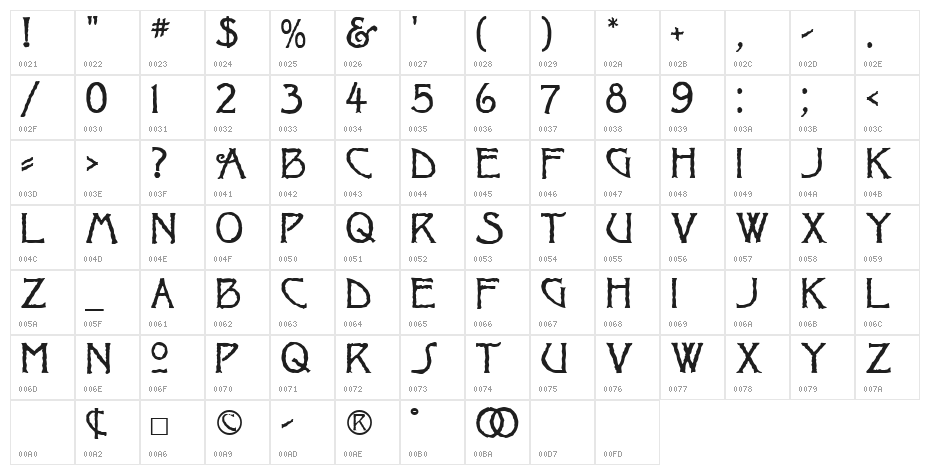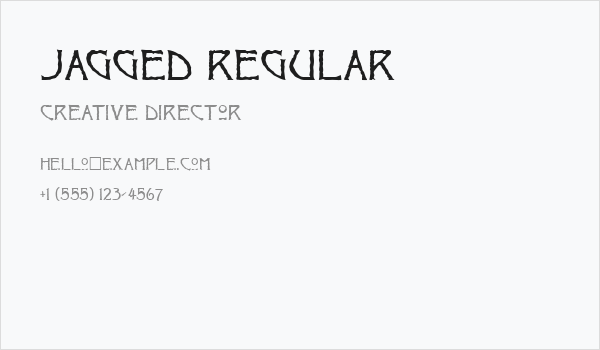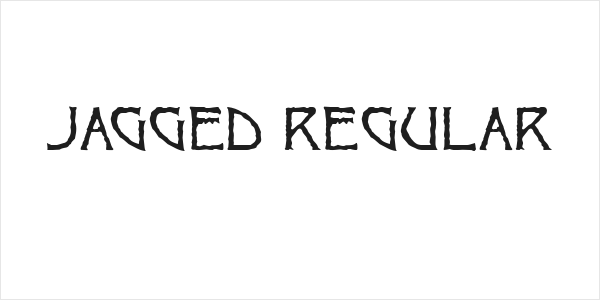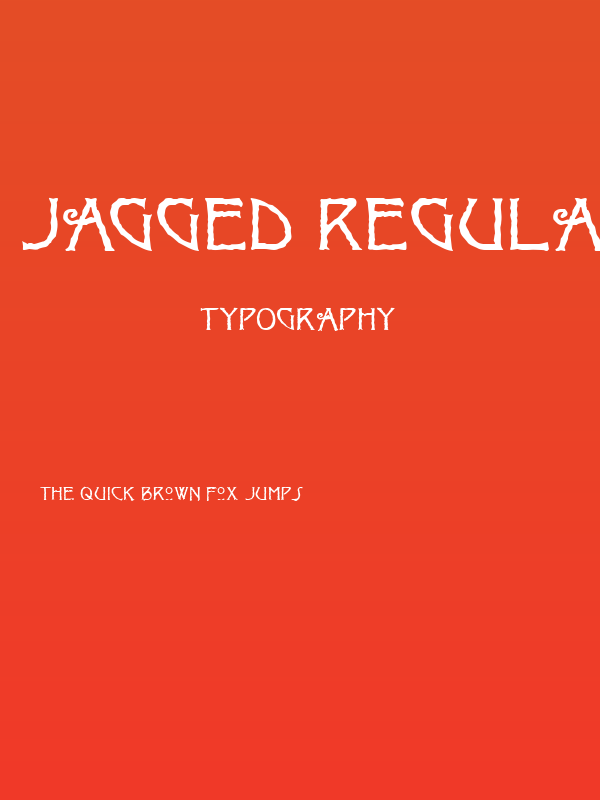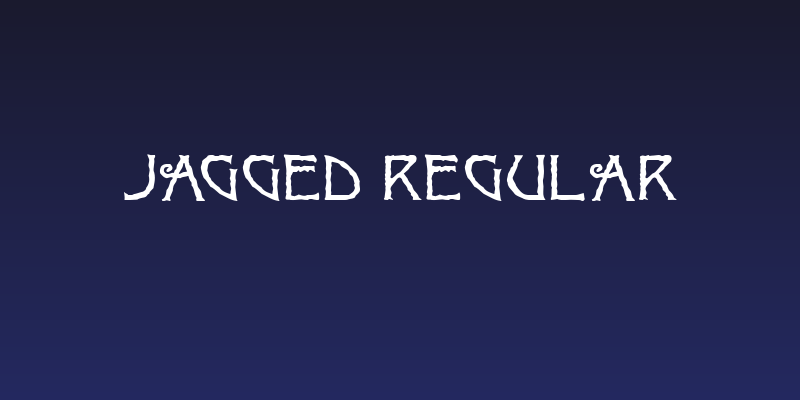
Jagged Regular Font
Fonts by Rick Mueller
| Proiecte propuse | Ideal for projects that require a bold, artistic touch, such as posters, album covers, or branding for edgy or alternative products. |